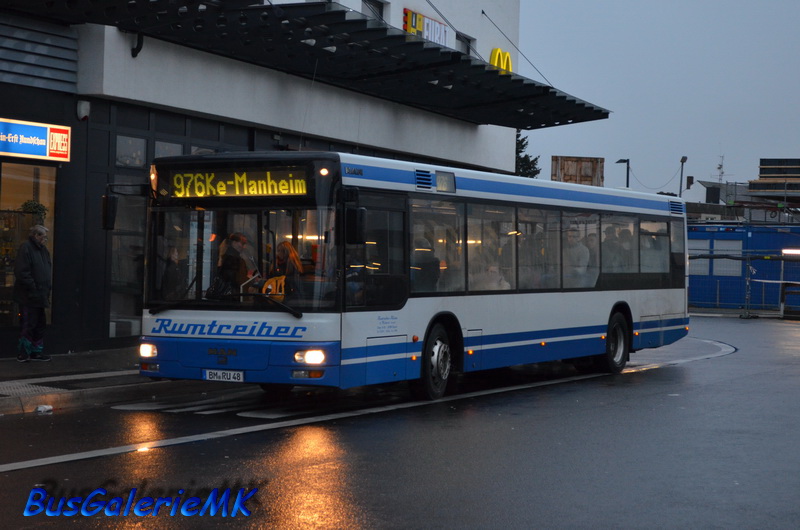
Schriftart eines Busunternehmens gesucht
Hier oder hier was dabei?
Von der Art her geht es in die richtige Richtung, die genaue Schriftart ist allerdings noch nicht dabei
Und beim Nachbau könnte man gleich darauf achten, es nicht ganz so sehr nach Rumtceihec aussehen zu lassen.